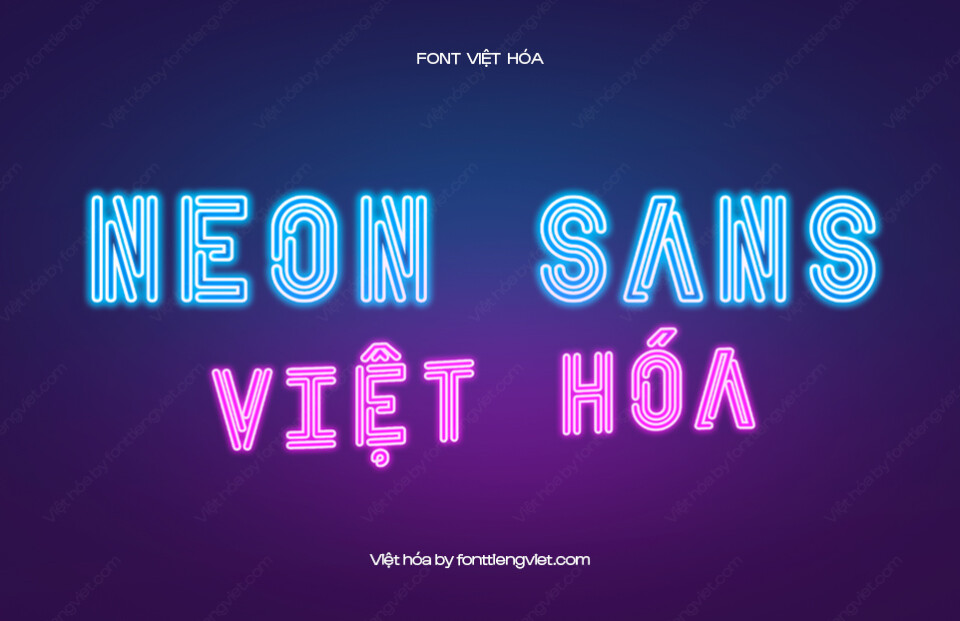
Font Việt hóa 1FTV VIP Neon Sans
Font Việt hóa 1FTV VIP Neon Sans: Sự Lựa Chọn Hoàn Hảo Cho Thiết Kế Hiện Đại
Giới thiệu về Font Việt hóa 1FTV VIP Neon Sans
Trong thế giới đồ họa kỹ thuật số hiện nay, việc tìm kiếm một bộ Font Miễn Phí chất lượng cao là nhu cầu thiết yếu của các nhà thiết kế. Font Việt hóa 1FTV VIP Neon Sans nổi lên như một giải pháp tối ưu nhờ phong cách hiện đại và sự tinh tế trong từng đường nét. Đây là bộ font sans-serif không chân được tối ưu hóa hoàn toàn cho bảng mã tiếng Việt, giúp người dùng không còn lo lắng về lỗi hiển thị dấu hay khoảng cách ký tự. Với thiết kế tối giản nhưng không kém phần sang trọng, bộ font này mang lại cảm giác chuyên nghiệp cho mọi tác phẩm.
Đặc điểm nổi bật của bộ font chữ VIP
Thiết kế hiện đại và linh hoạt
Đặc điểm nổi bật nhất của Font Việt hóa 1FTV VIP Neon Sans chính là cấu trúc hình học cân đối. Các nét chữ được trau chuốt tỉ mỉ, tạo nên sự đồng nhất dù bạn sử dụng ở định dạng in ấn hay hiển thị trên màn hình. Font chữ này rất phù hợp để làm tiêu đề cho các trang web công nghệ, bìa sách giáo khoa hoặc các ấn phẩm truyền thông trong môi trường học đường.
Khả năng ứng dụng đa dạng
Không chỉ dừng lại ở các thiết kế phẳng, bộ font này còn cực kỳ nổi bật khi kết hợp với các hiệu ứng ánh sáng như đèn neon hay đổ bóng. Nhờ độ dày nét vừa phải, Font Việt hóa 1FTV VIP Neon Sans duy trì được độ đọc tốt ngay cả ở kích thước nhỏ, hỗ trợ đắc lực cho các bạn học sinh, sinh viên trong việc trình bày bài tập lớn hoặc làm slide thuyết trình sinh động.
Kết luận về Font Việt hóa 1FTV VIP Neon Sans